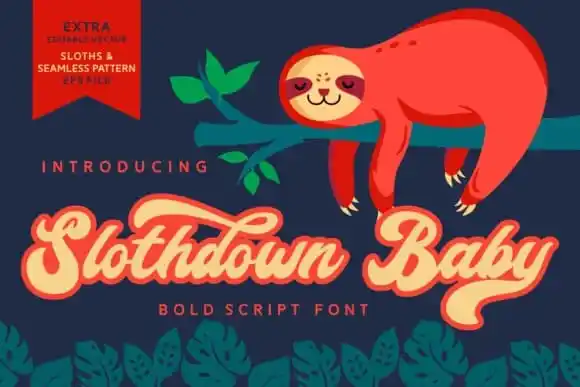
Slothdown Baby Script Font – Fonte Grátis
Slothdown Baby Script Font
A Slothdown Baby Script Font é uma elegante e amigável tipografia script que se destaca para todas as idades. Inspirada nas serpentes, essa fonte irá brilhar em vários projetos futuros de você. É perfeita para títulos de filme, logotipos, blogs, identidades corporativas, títulos de livros, mídia social, marcas e até mesmo cartões de aniversário ou outros eventos especiais. Seja ela a sua próxima adição à arsenal de design, esta fonte certamente será um recurso valioso para qualquer projeto criativo que você esteja desenvolvendo no futuro. A Slothdown Baby Script Font é o tipo certo para fazer seus projetos serem inesquecíveis e impecáveis.